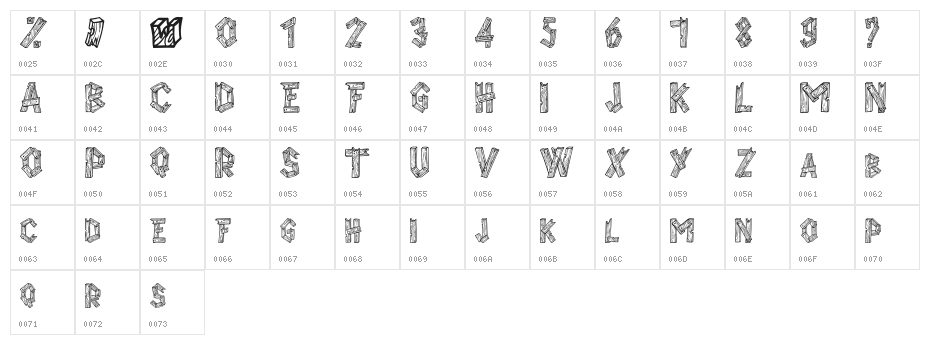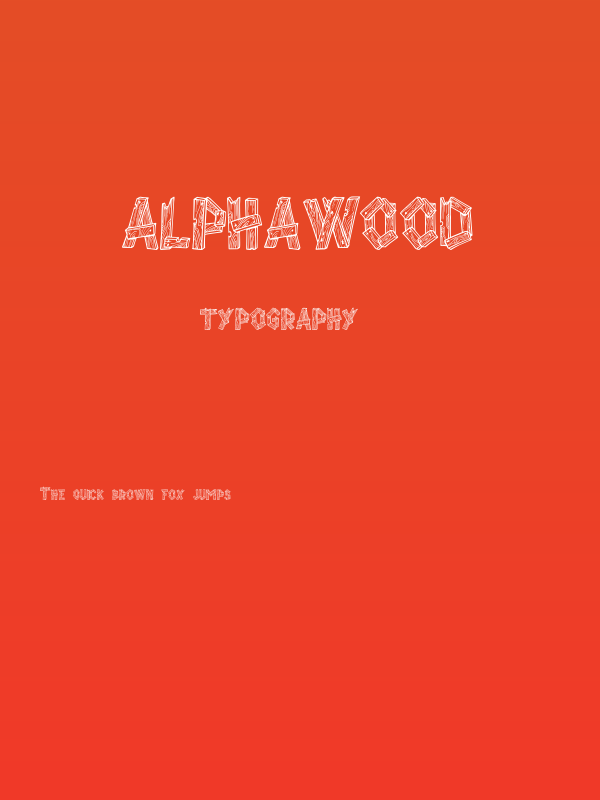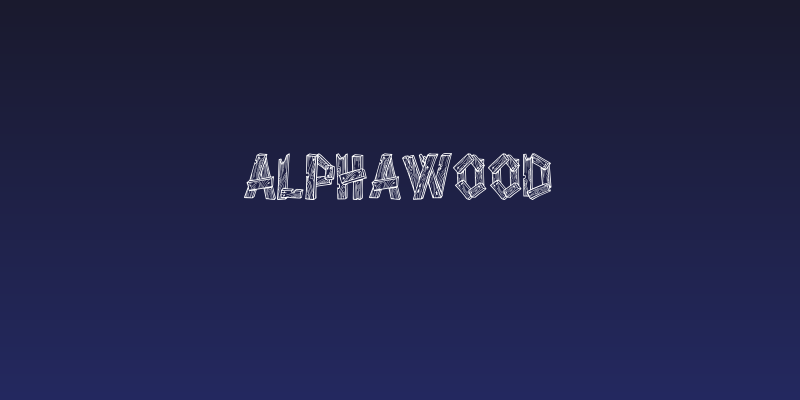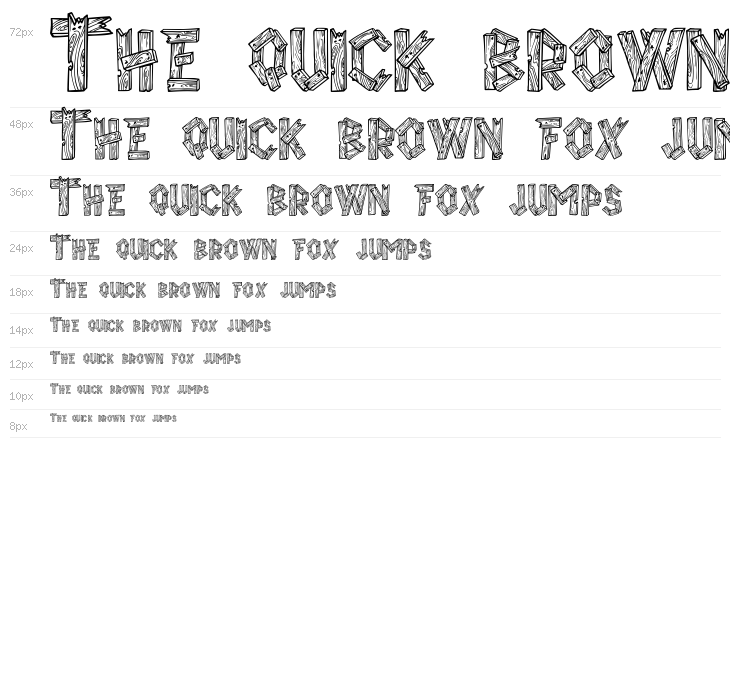
AlphaWood Font
| Estilo general | Rustic, Organic, Natural |
| Caso de uso | Logos, Headlines, Posters |
| Proyectos propuestos | Ideal for nature-themed posters, eco-friendly brand logos, outdoor event invitations, and rustic signage. |